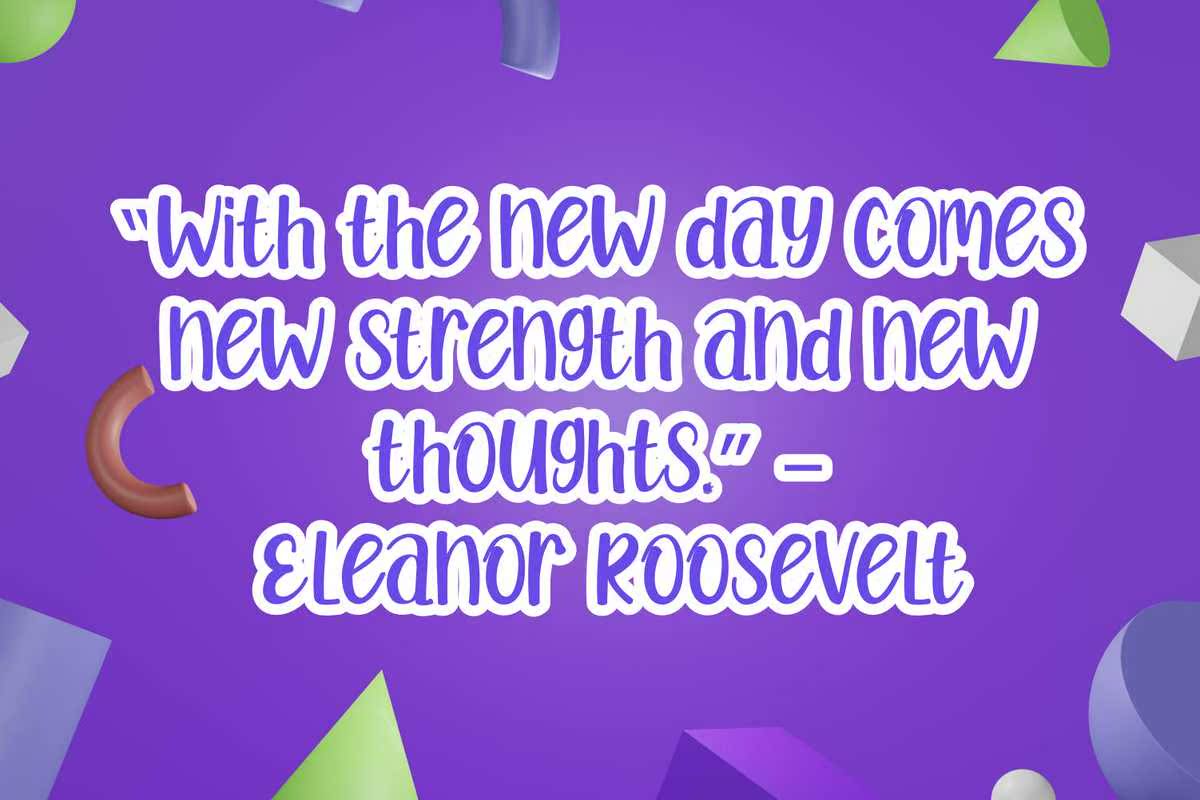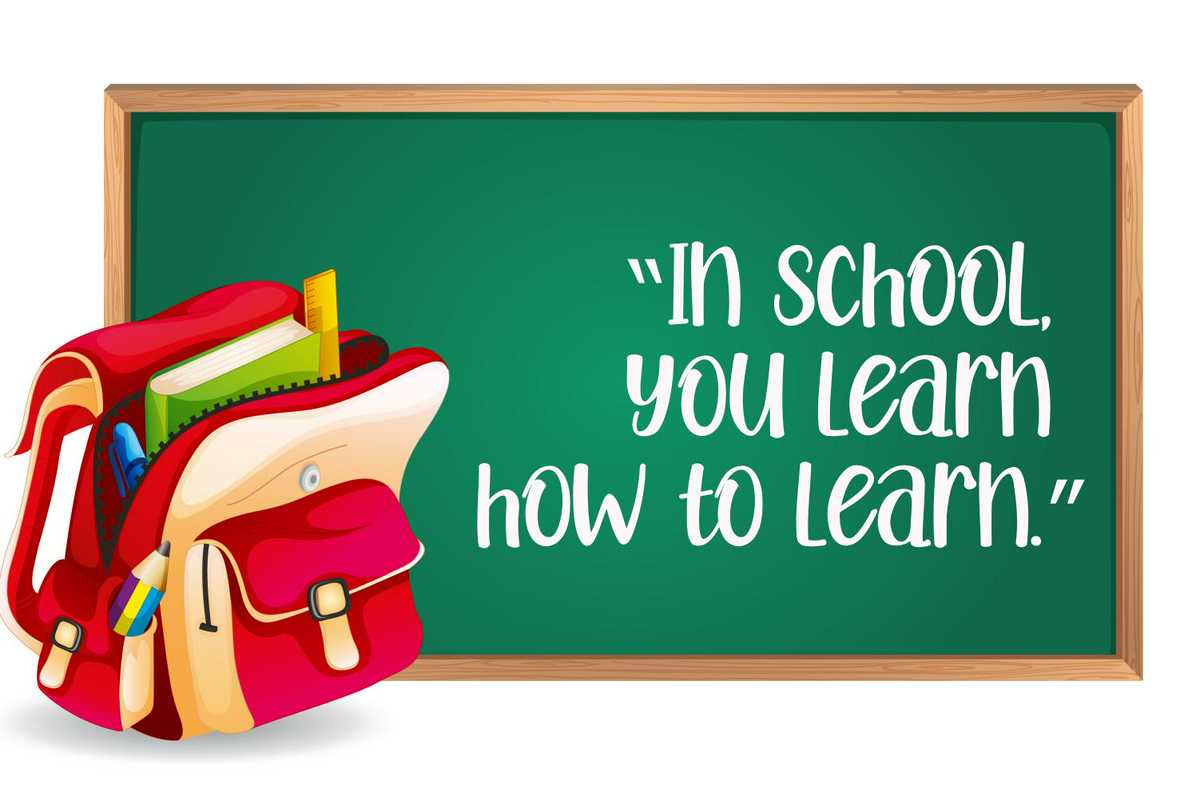
Bellayears是一种友好的手写字体。这种令人眼花缭乱的书写字体将把任何创造性的想法转变为现实。它的自然和独特的风格使其成为一个巨大的设计池。从它的真实感受中获得灵感,并用它来美化婚姻生活、美化家庭、吸引眼球的社会和谐,还有剪彩。唯一的限制就是你的想象力!Bellayears是一种友好的手写字体。这种令人眼花缭乱的书写字体将把任何创造性的想法转变为现实。它的自然和独特的风格使其成为一个巨大的设计池。从它的真实感受中获得灵感,并用它来美化婚姻生活、美化家庭、吸引眼球的社会和谐,还有剪彩。唯一的限制就是你的想象力!